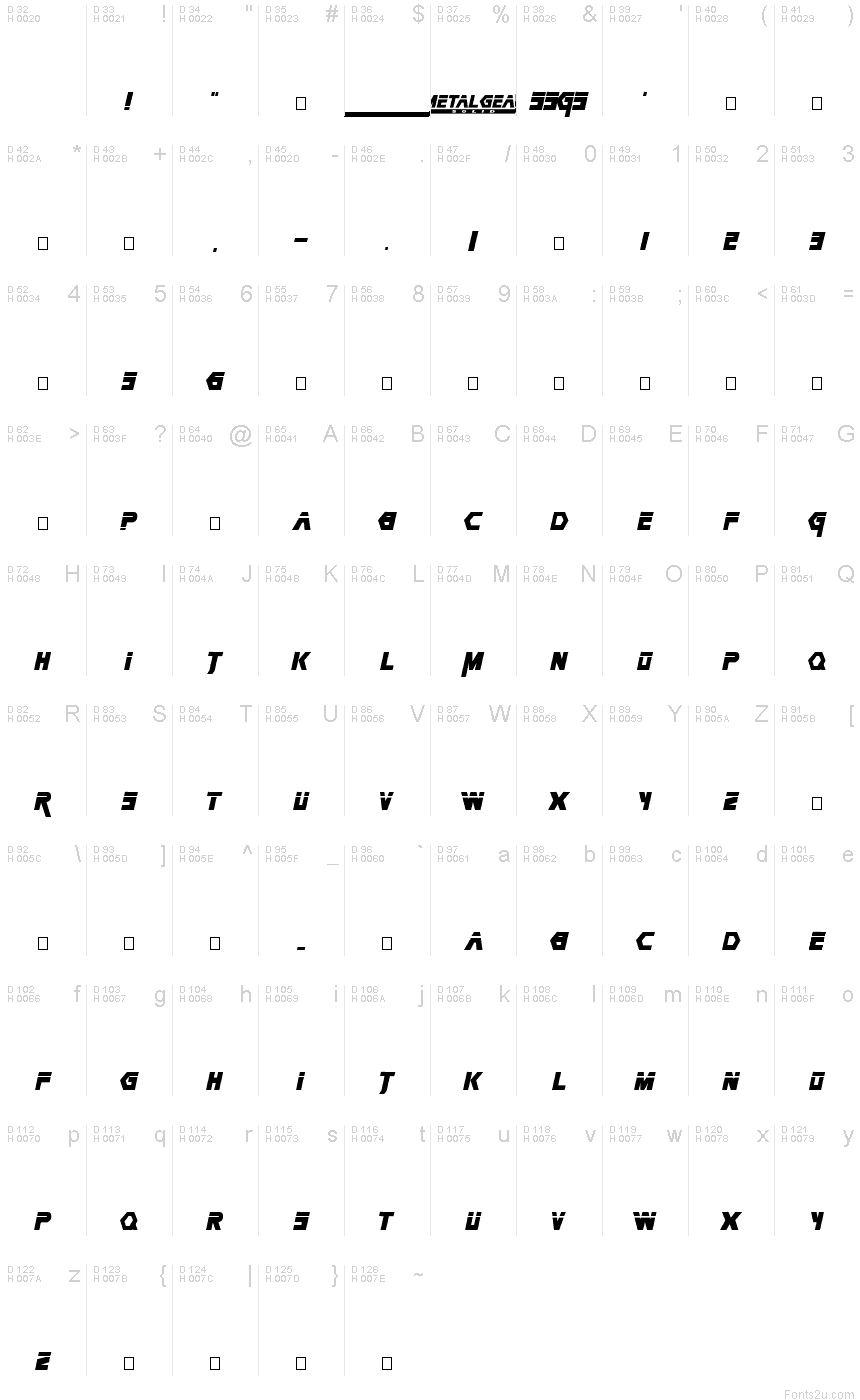
Metal Gear
Metal Gear di Steve Snape è un carattere display di stampo techno, caratterizzato da una silhouette inclinata, quasi tagliata a blocchi, con angoli vivi a forma di cuneo. Le lettere conservano una solida presenza industriale, mentre i tagli angolari e gli spazi interni aperti conferiscono al design un tocco futuristico e criptato.
Metal Gear è perfetto per poster sci-fi, titoli di videogiochi, loghi, banner per interfacce e brevi titoli editoriali che richiedono un tono meccanico e deciso. Il ritmo angolare favorisce una lettura compatta come un’unica linea grafica, rendendolo ideale anche per copertine di album, segnaletica per eventi e progetti di branding che puntano su uno stile snello e ingegneristico.